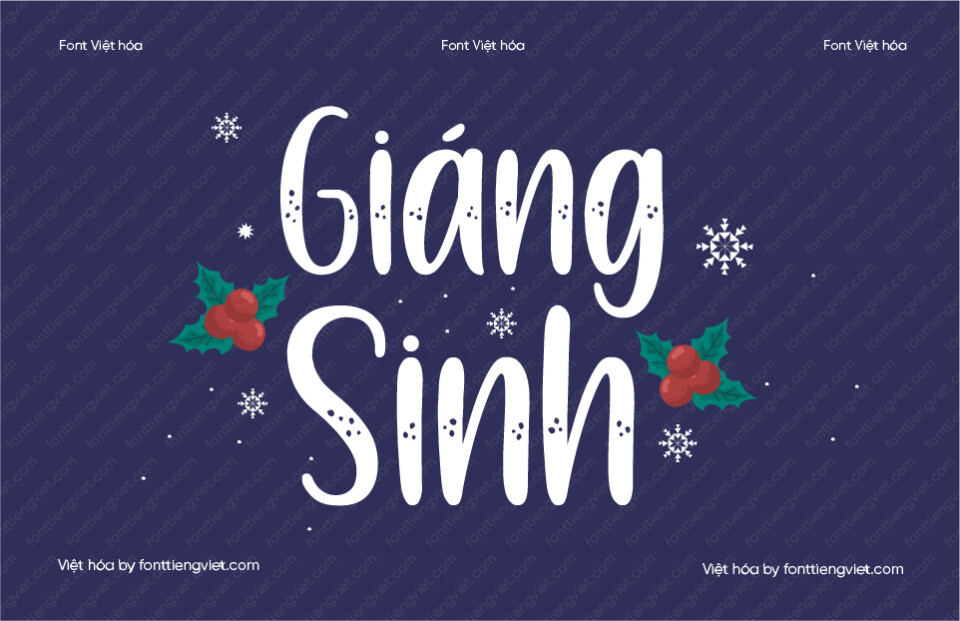
Font Việt hóa 1FTV VIP Snowy Christmas
Font Việt hóa 1FTV VIP Snowy Christmas là lựa chọn hoàn hảo cho các thiết kế mùa lễ hội như banner Noel, thiệp chúc mừng, poster, menu và nội dung mạng xã hội. Font mang phong cách tuyết rơi mềm mại, nổi bật khi kết hợp cùng màu đỏ – xanh – trắng. Tải nhanh, dùng dễ, hỗ trợ tiếng Việt đầy đủ và phù hợp cả in ấn lẫn thiết kế digital.
Font Việt hóa 1FTV VIP Snowy Christmas – Font Noel đẹp cho thiết kế mùa lễ hội
Mùa Giáng Sinh là thời điểm “vàng” để tạo ra những thiết kế ấn tượng: banner khuyến mãi, poster sự kiện, thiệp chúc mừng hay hình ảnh social. Và để tăng cảm xúc lễ hội, việc chọn đúng font chữ là cực kỳ quan trọng. Font Việt hóa 1FTV VIP Snowy Christmas mang phong cách tuyết phủ – mềm mại, vui tươi, giúp thiết kế của bạn nổi bật ngay từ cái nhìn đầu tiên.
Giới thiệu Font 1FTV VIP Snowy Christmas
1FTV VIP Snowy Christmas là font trang trí chủ đề Noel với các nét chữ bo tròn, có cảm giác “phủ tuyết” hoặc họa tiết mùa đông. Font được Việt hóa đầy đủ giúp bạn gõ tiếng Việt dễ dàng, hạn chế lỗi dấu khi làm tiêu đề, câu chúc, slogan hoặc tên chiến dịch.
Điểm nổi bật của Font Việt hóa Snowy Christmas
• Phong cách Noel rõ rệt: tạo không khí lễ hội, ấm áp và vui tươi.
Ứng dụng thực tế
Để dùng font hiệu quả, bạn nên ưu tiên font này cho tiêu đề, headline hoặc các đoạn chữ ngắn mang tính trang trí. Với nội dung dài, hãy phối hợp thêm một font sans-serif dễ đọc để tổng thể hài hòa và chuyên nghiệp hơn.